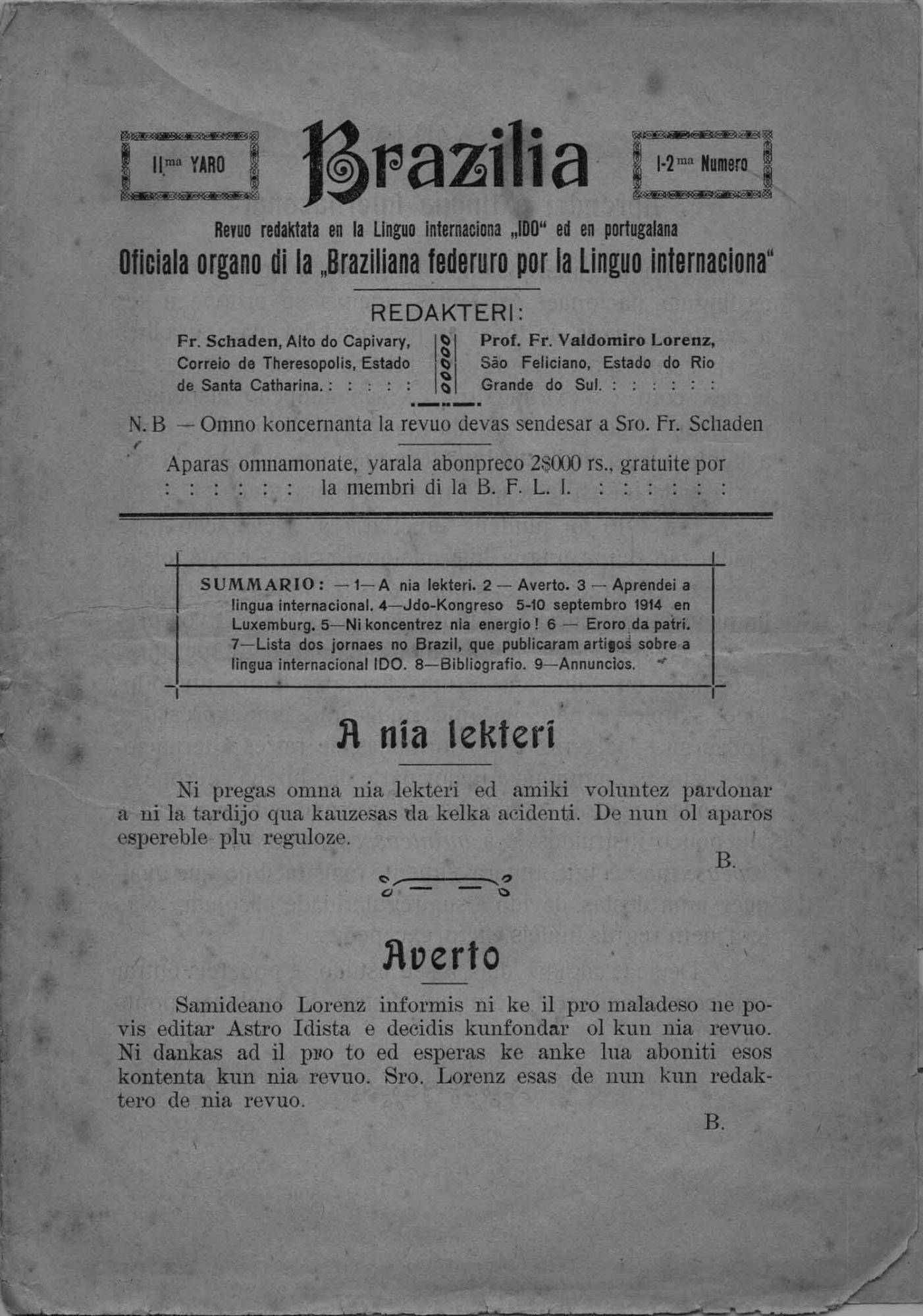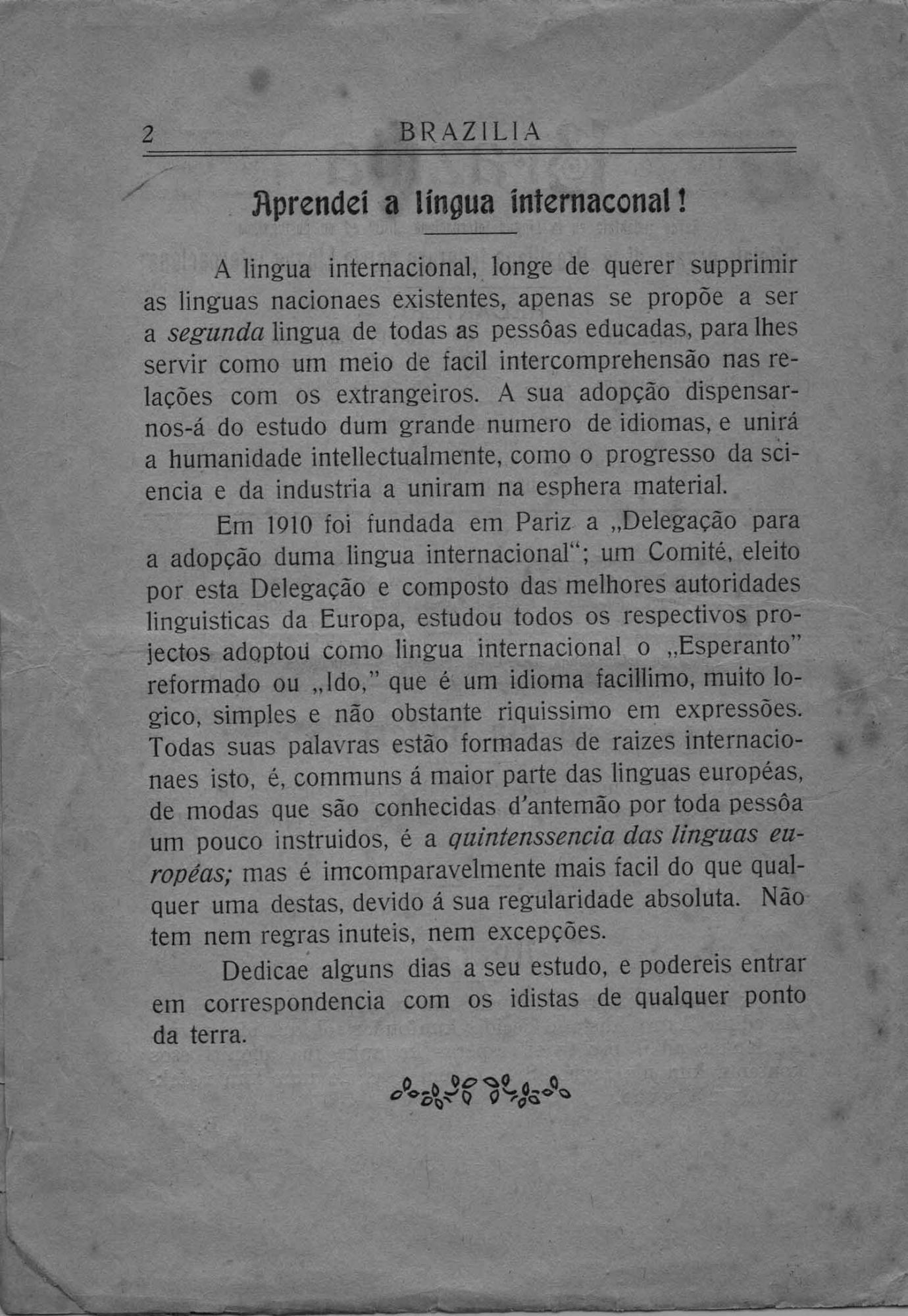
Ido Linguo Schriftart von 1914
ich habe ein Dokument der "Ido Linguo" bekommen.
Nun suche ich die Schritart für die Überschriften.
Für den Text habe ich bereits eine passende gefunden, die Romana EF von Elsner+Flake.
Hat jemand eine Idee?
DIese Schrift heißt im Original Hougton entworfen von Herman Ihlenburg
für die Gießerei MacKellar in Philadelphia.
In Deutschland lieferbar unter den Namen:
Edison, Kosmos, Nero, Markoni oder Tasso.
Siehe Seemanns Handbuch der Schriftarten.